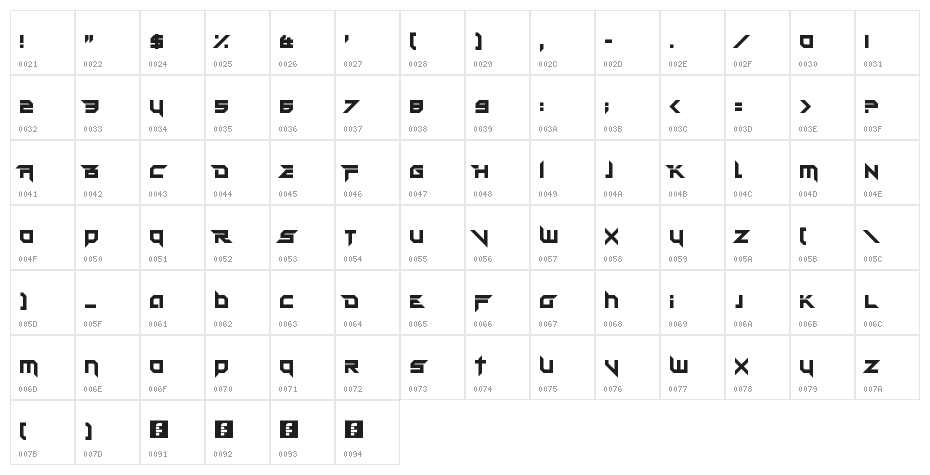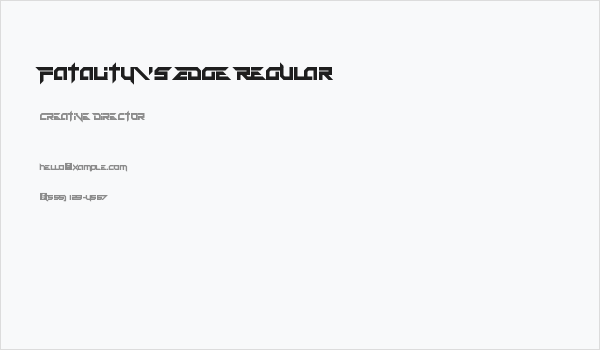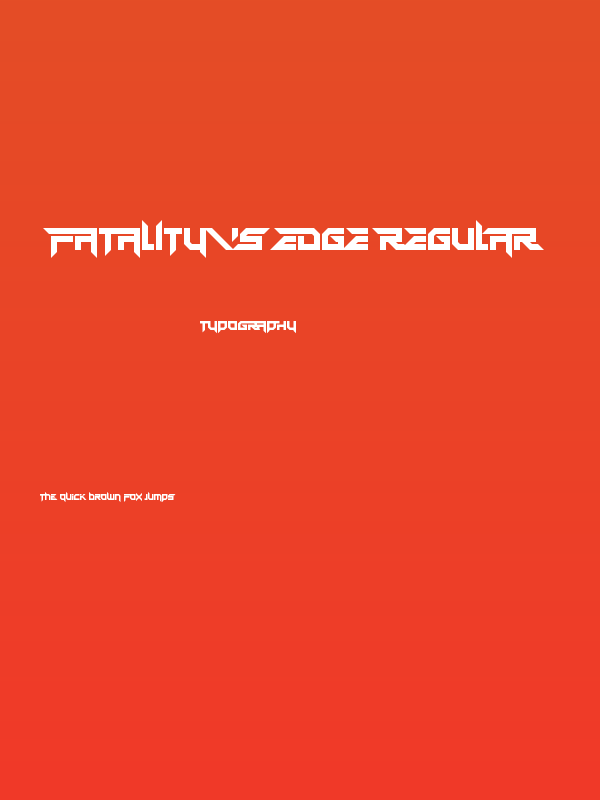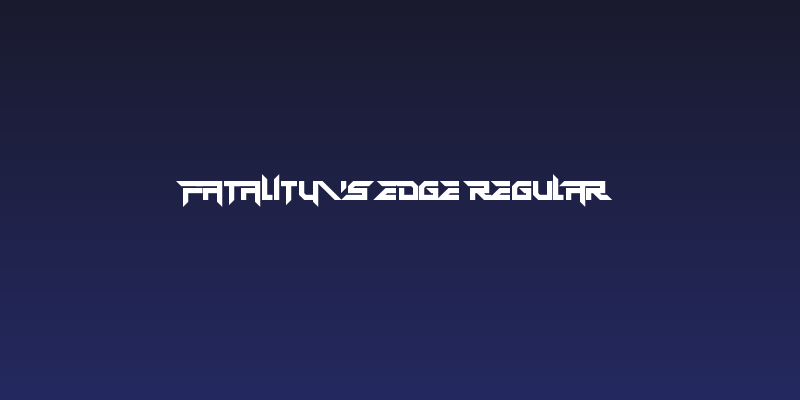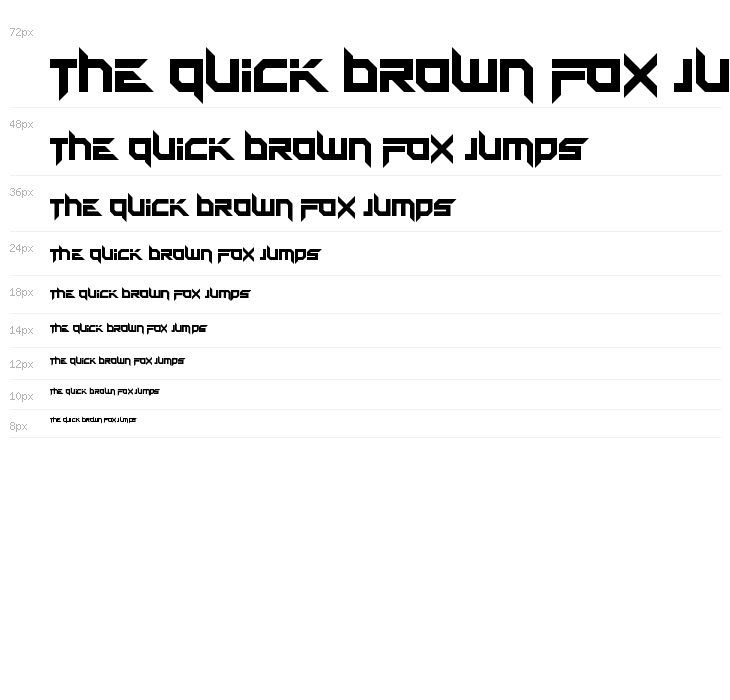
Fatality's Edge Regular Font
| Stile generale | Futuristic |
| Progetti proposti | Ideal for sci-fi themed projects, video game titles, movie posters, and branding that requires a modern, cutting-edge look. |
Fatality's Edge Regular